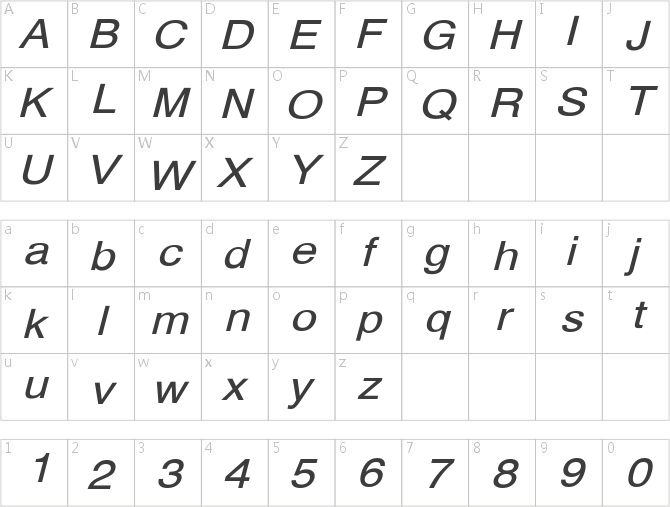
HelveticaExtObl-Normal 詳情頁
HelveticaExtObl-Normal字體字庫(kù)是一款讓人賞心悅目、百看不厭的英文字體,適合各類廣告和產(chǎn)品包裝設(shè)計(jì)應(yīng)用,字體大小0.05MB,格式為ttf字體,上傳用戶是……西央,作者/版權(quán)方為未知